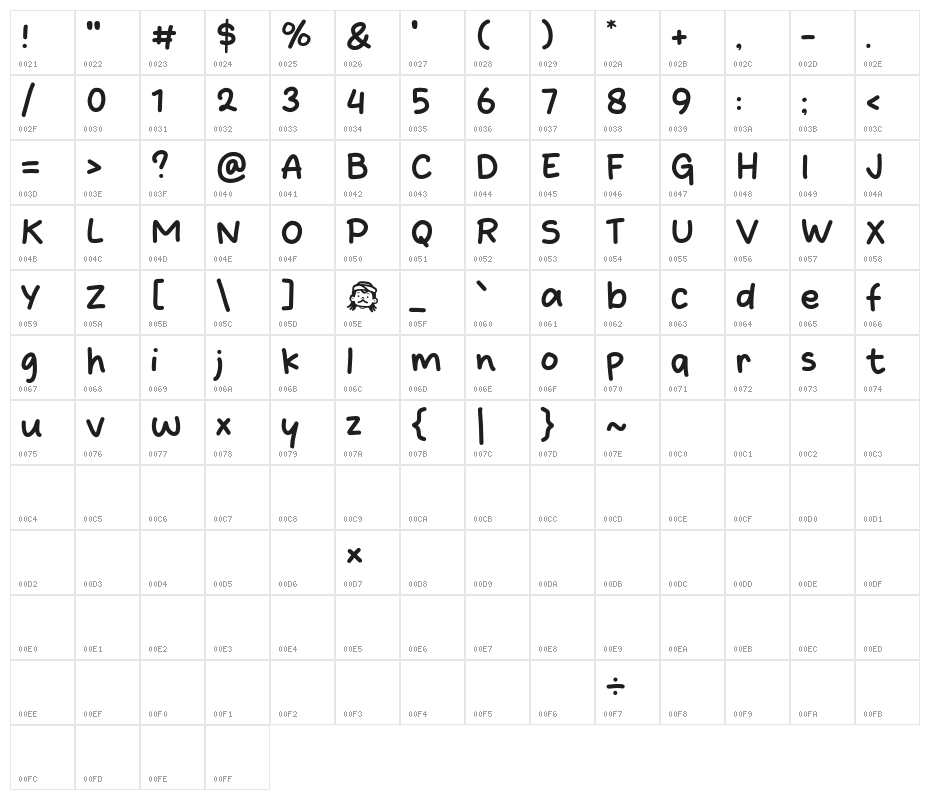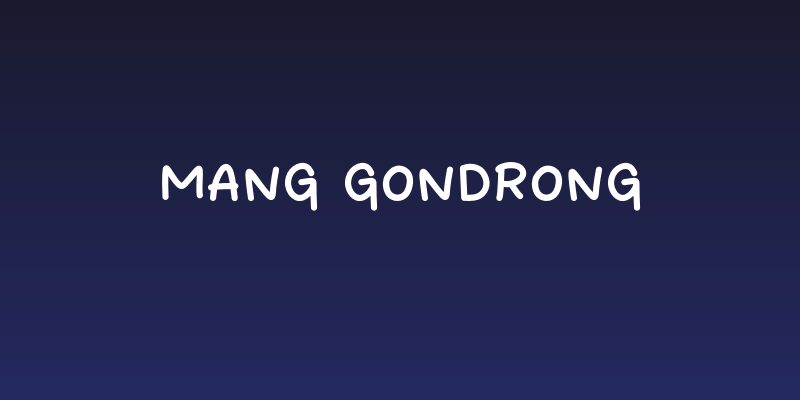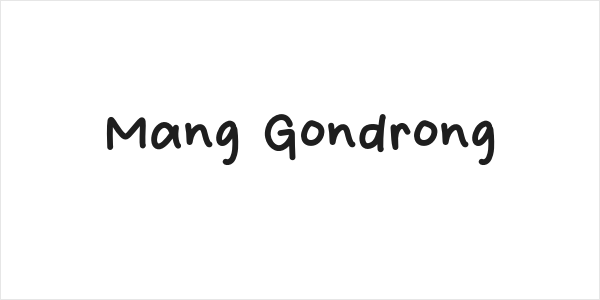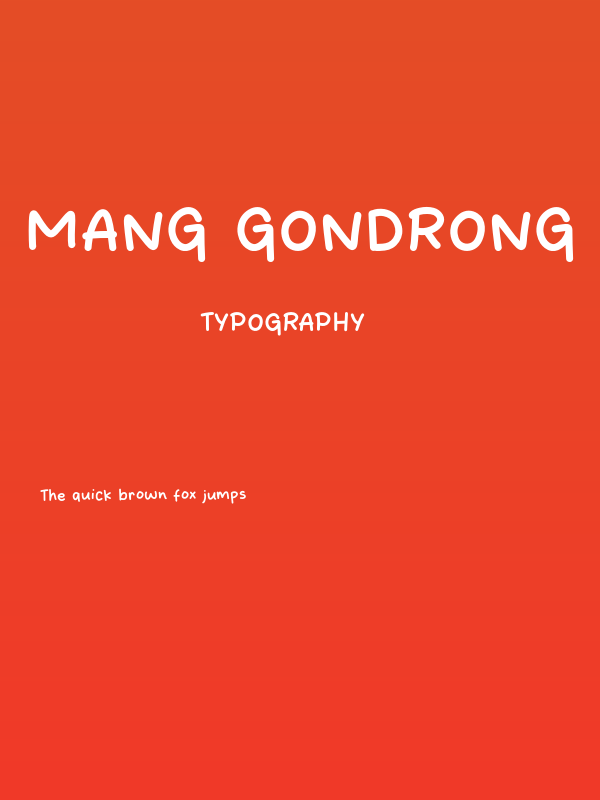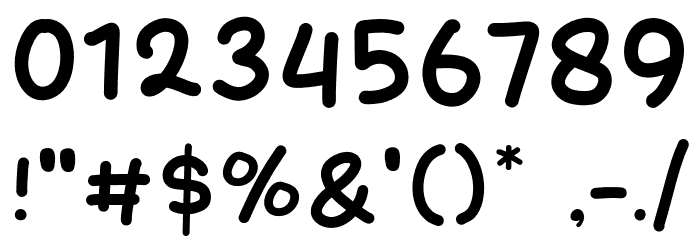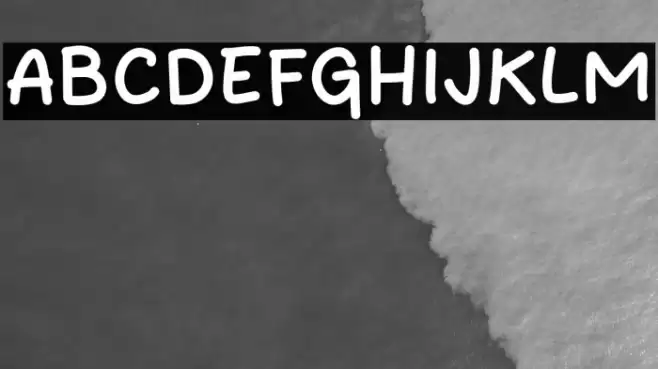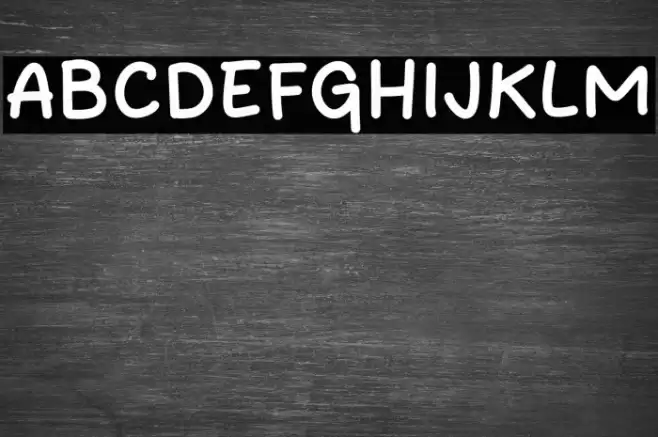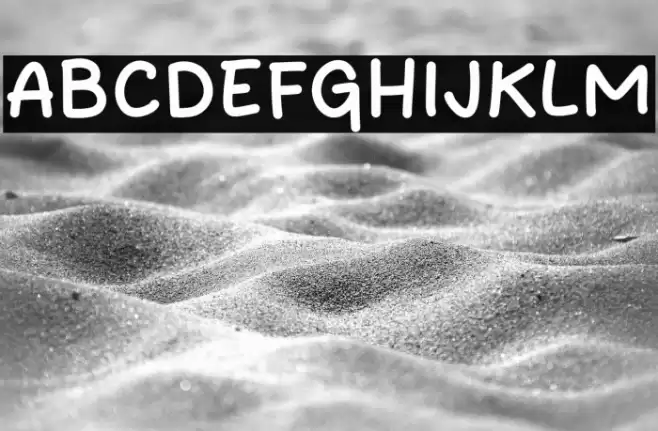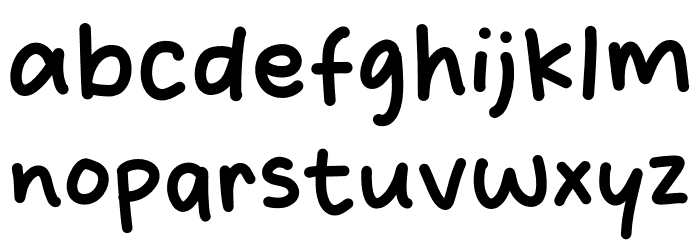
Mang Gondrong Font
| Gesamtstil | Casual, Playful |
| Anwendungsfall | Headlines, Informal text, Branding |
| Vorgeschlagene Projekte | Ideal for children's books, greeting cards, playful branding, and social media graphics. |